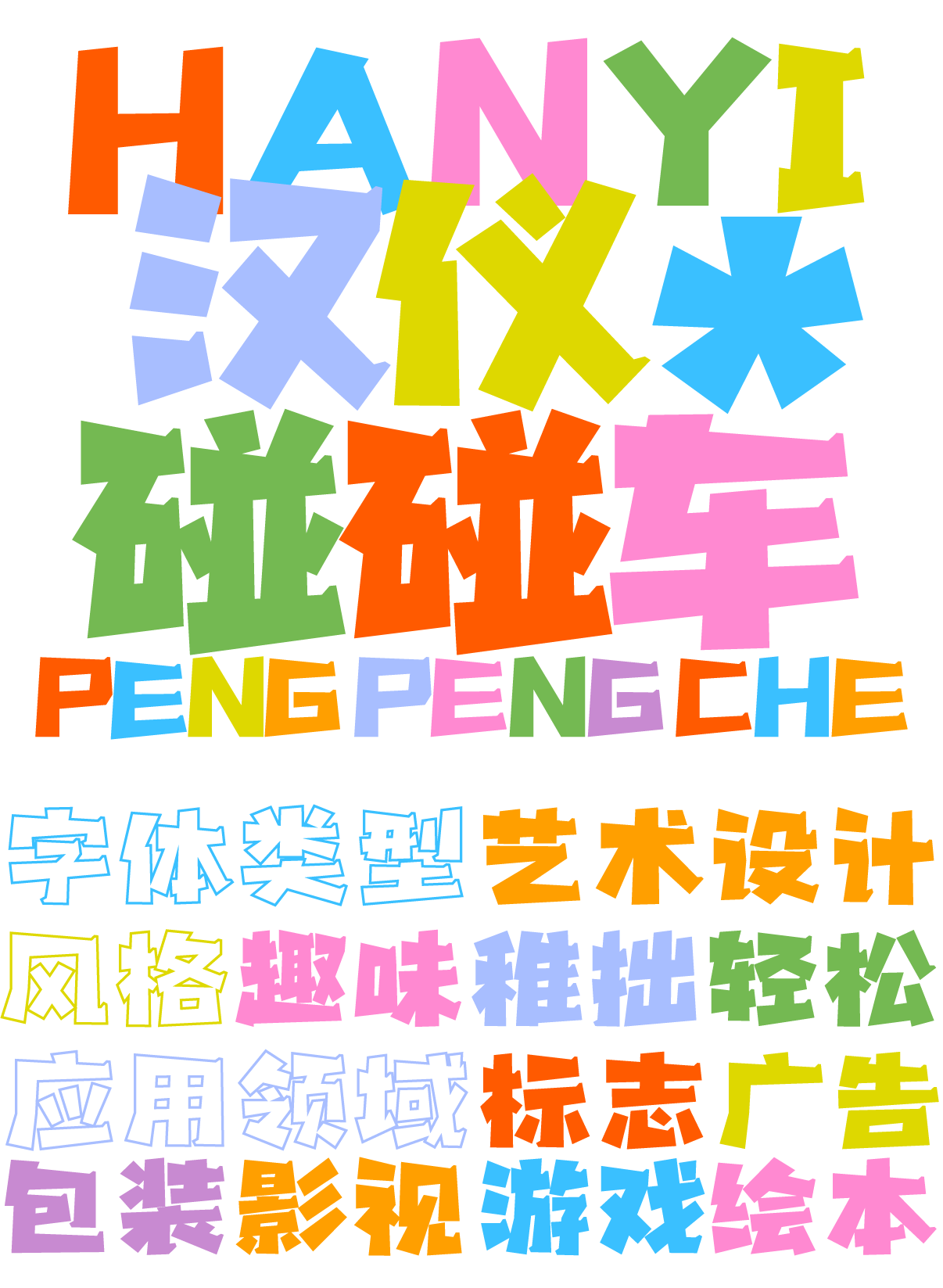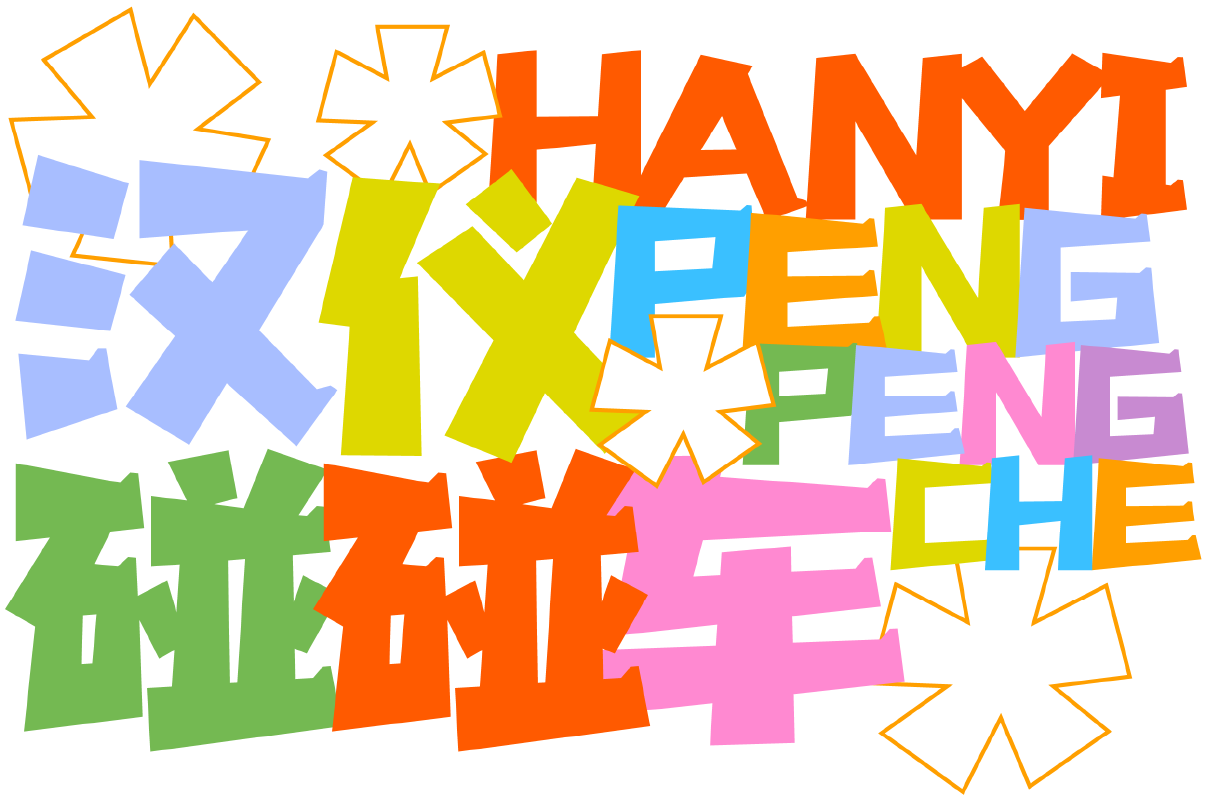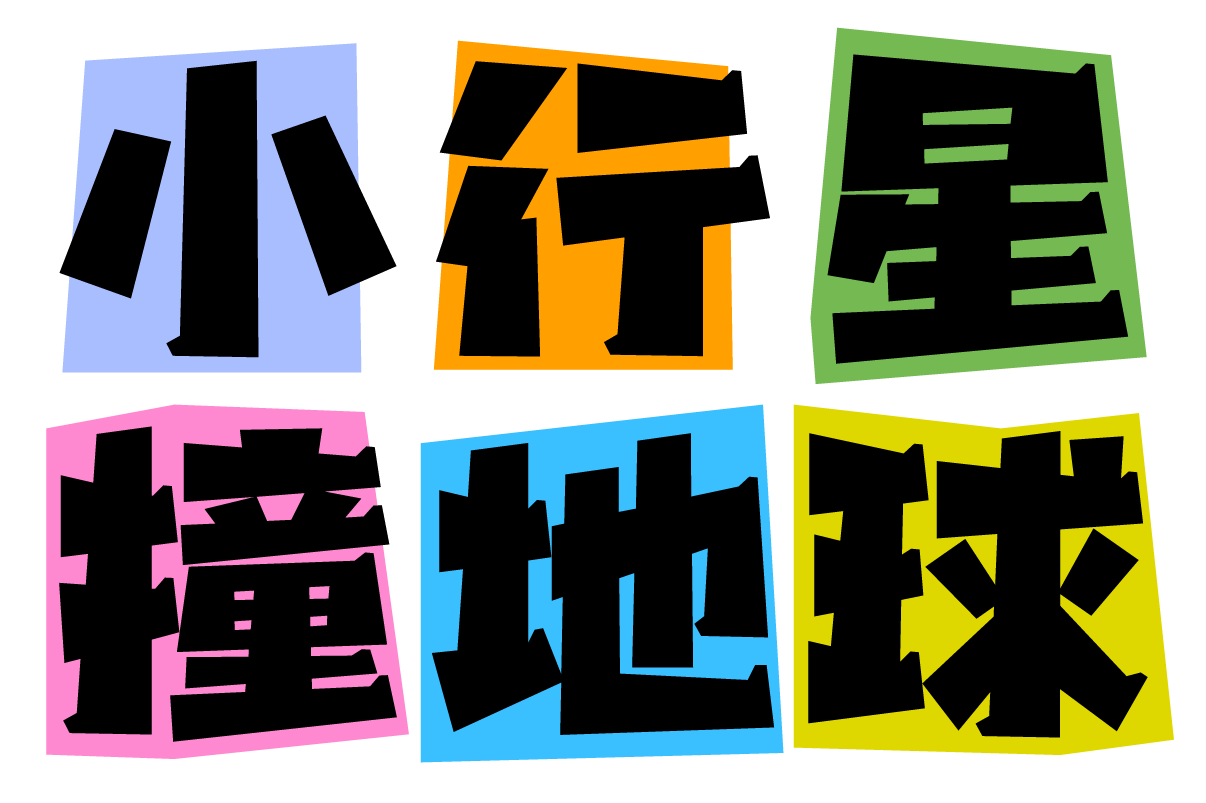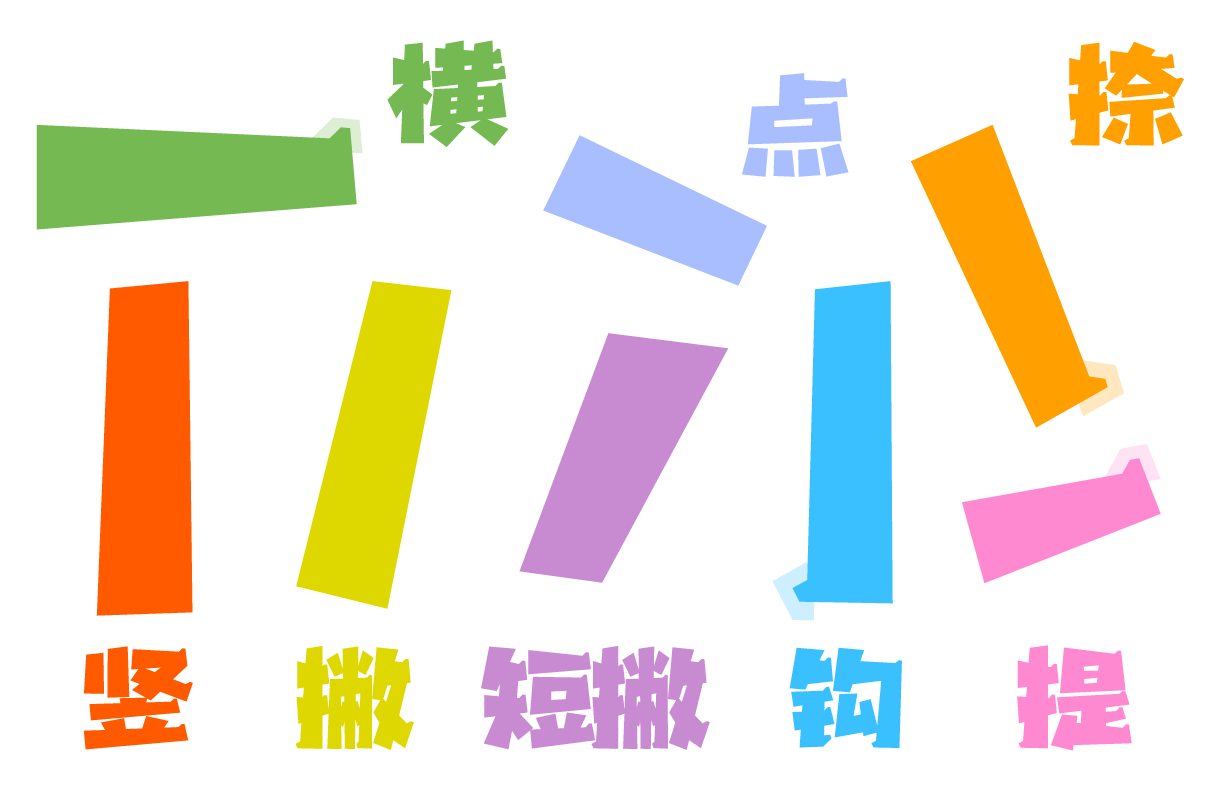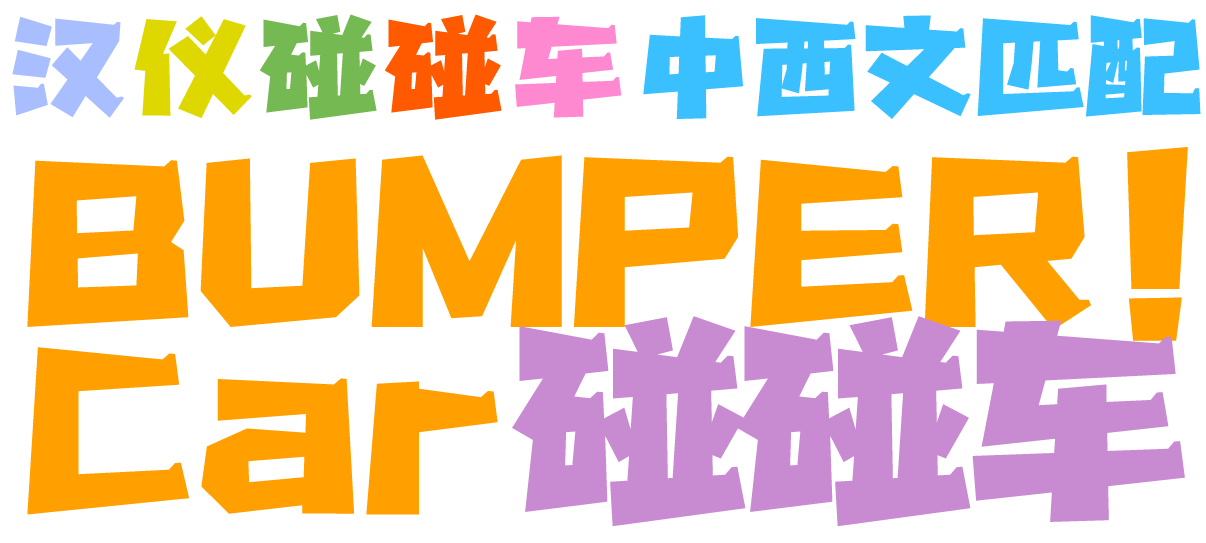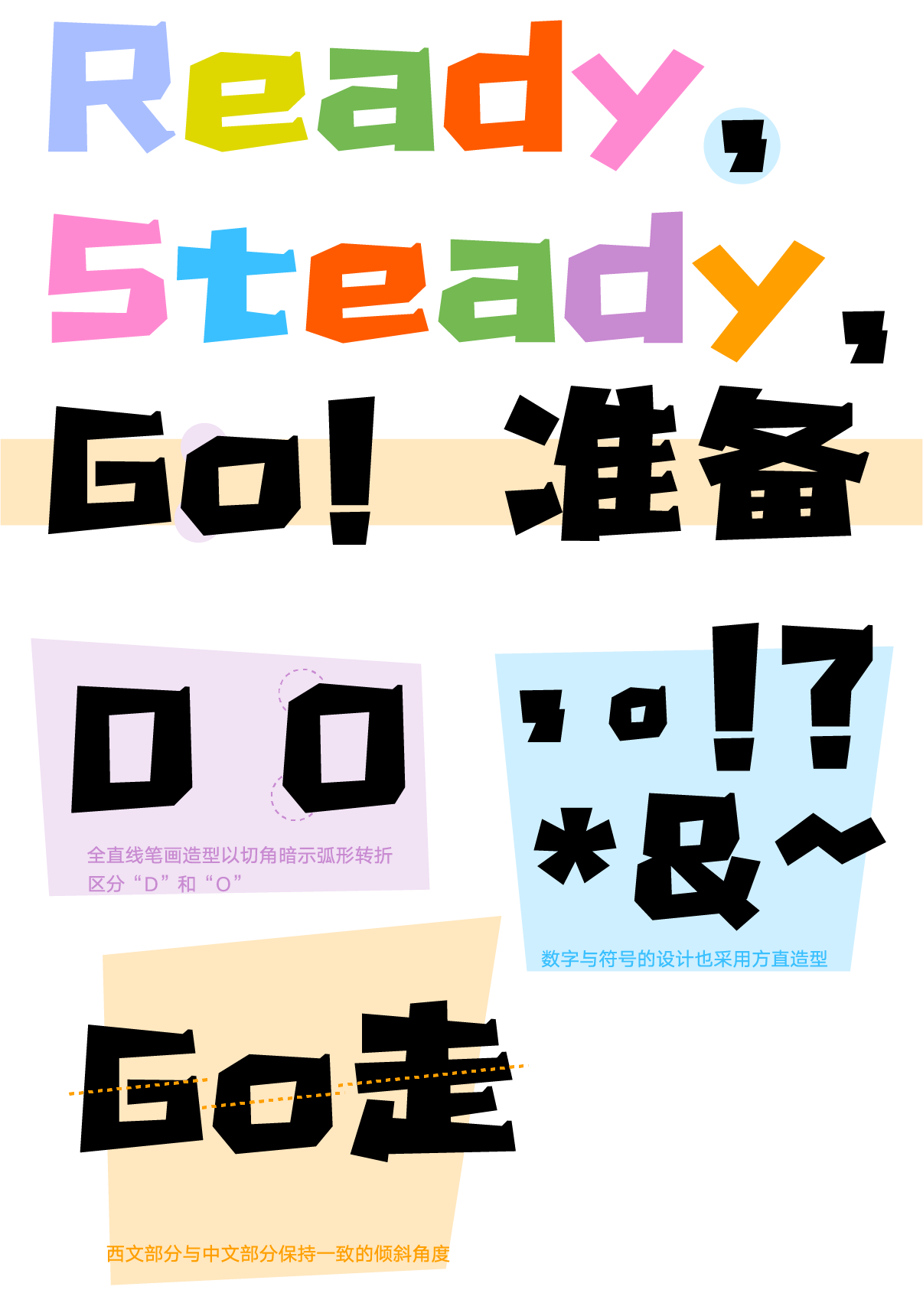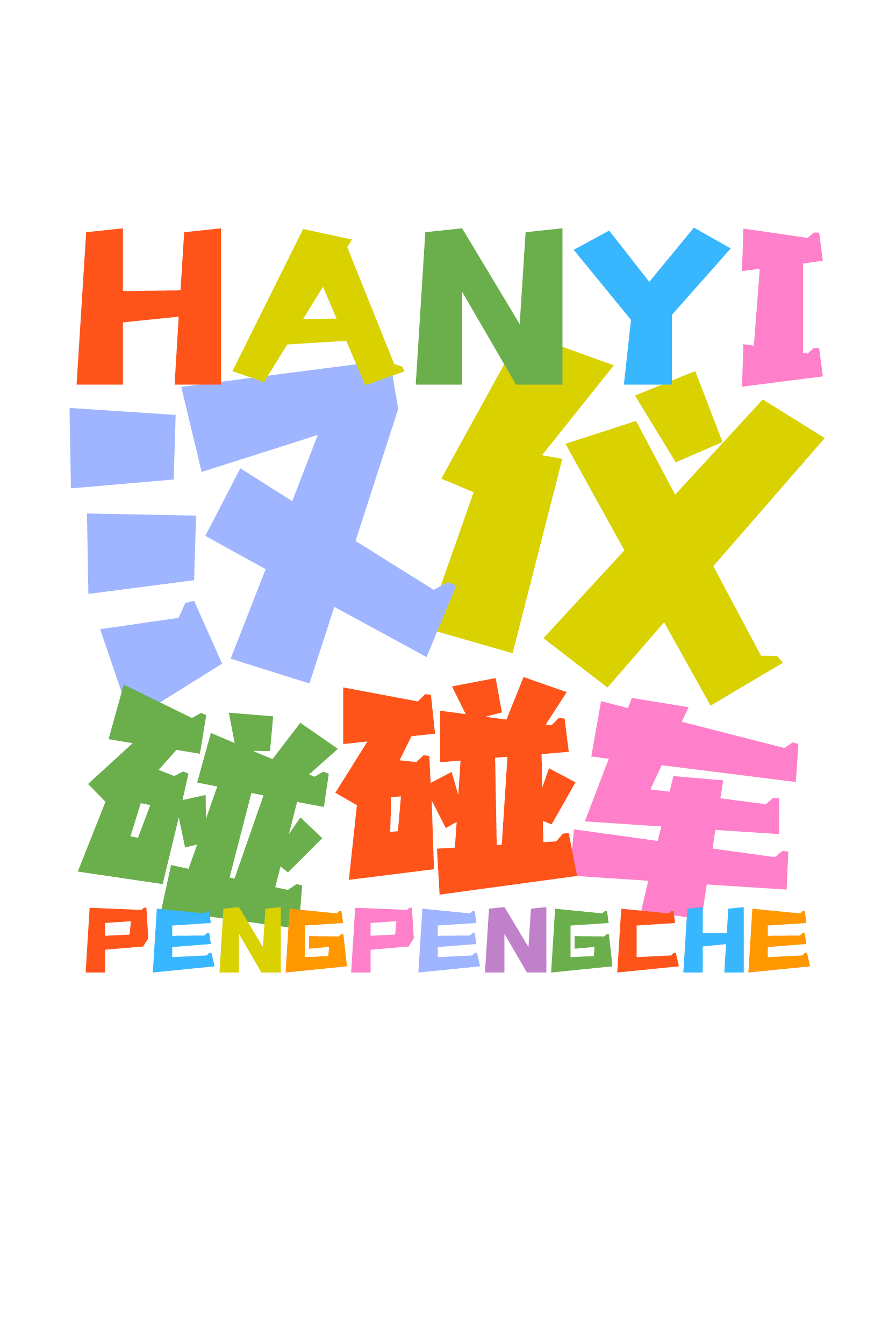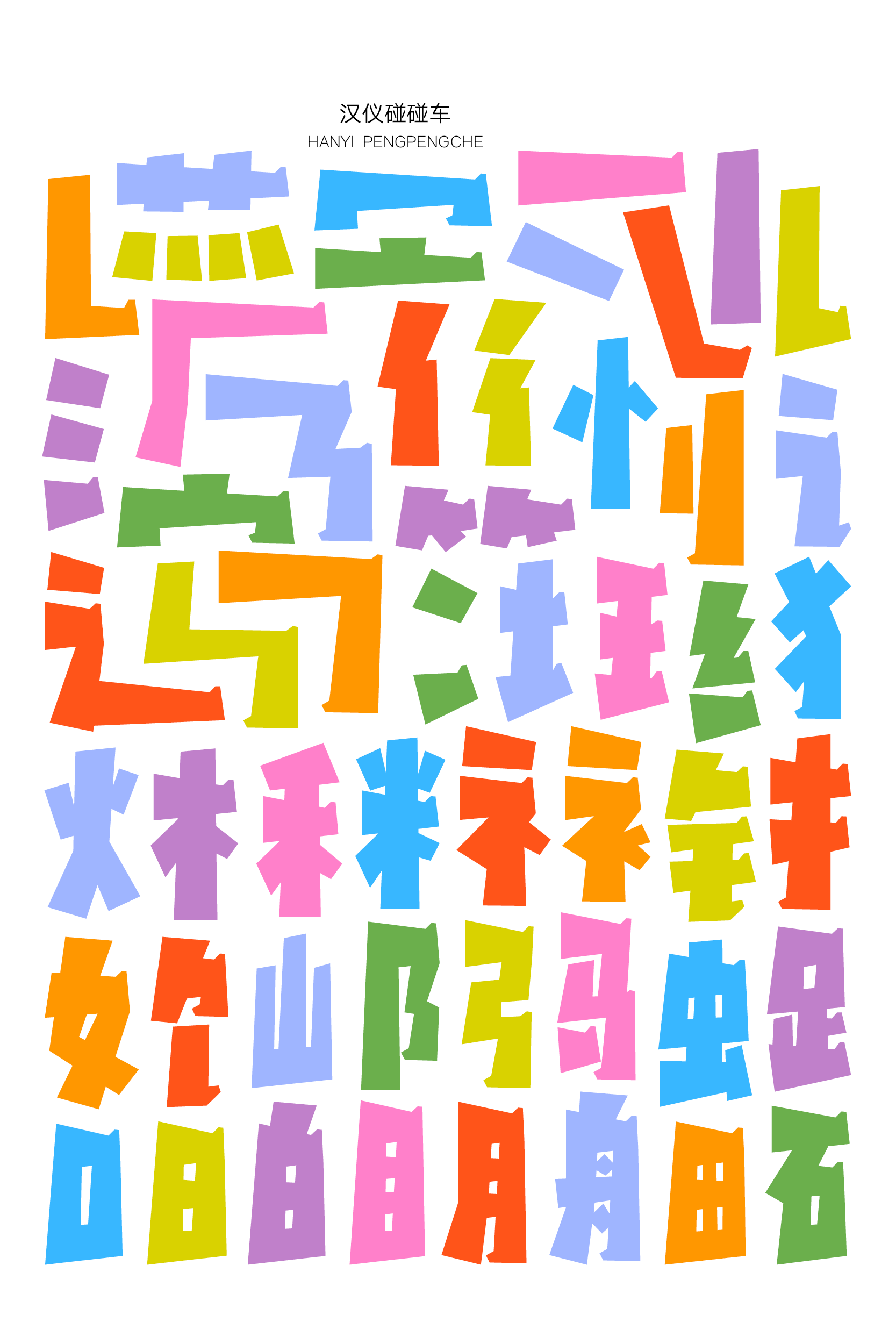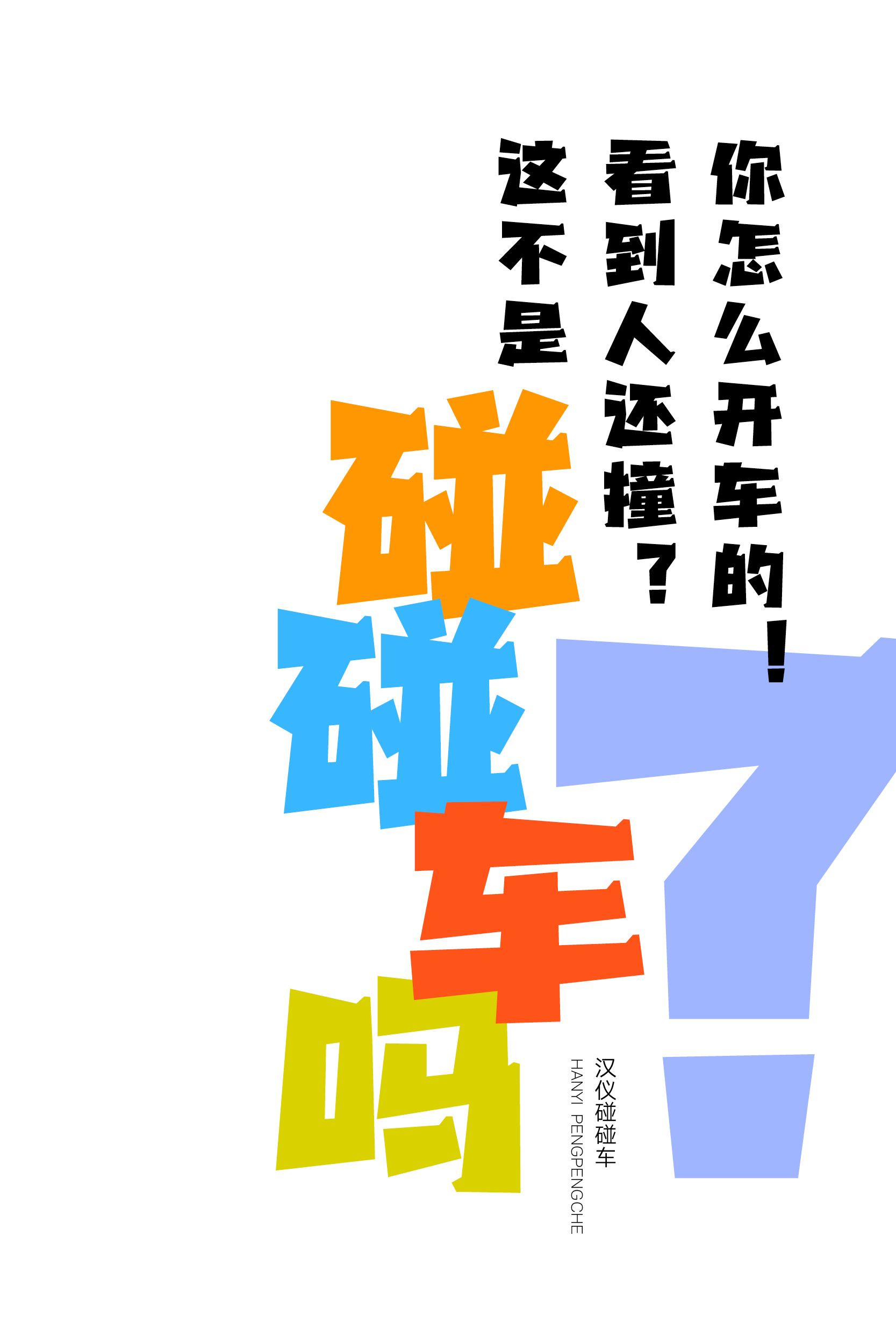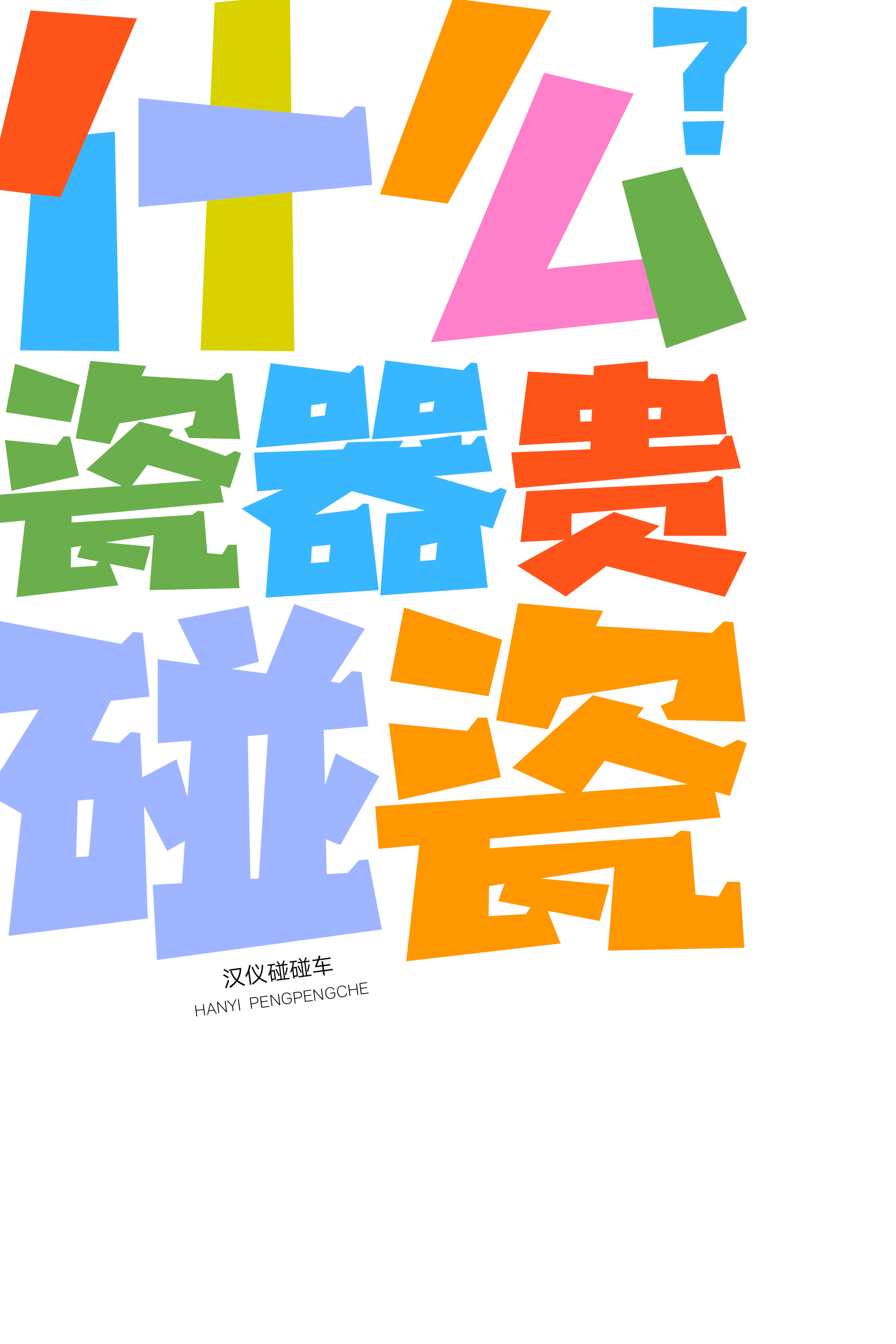
灵活多变,动感十足的趣味字体
嘟嘟——由汉仪字库签约作者李城君创作的汉仪碰碰车,来了!厚重有棱角的笔画横冲直撞,碰撞出稚拙俏皮的字形,整体硬朗而不尖利,灵活多变,动感十足,笔画的梯形装饰增加了趣味性。这款字体有着如同碰碰车一样的视觉冲击力,适合作为标题字体应用于游戏、动画、影视、绘本、漫画等多种场景,打造轻松快乐的游乐场。
字形轮廓灵活多变,动感十足。
全直线的笔画厚重有棱角,起收笔粗细对比明显,部分笔画的末端有梯形装饰。
“横冲直撞”的笔画碰撞出字形向右上倾斜的角度。
西文部分保留了方直厚重的全直线笔画造型和梯形装饰,字形俏皮可爱,中西文搭配使用碰撞出更多的趣味。